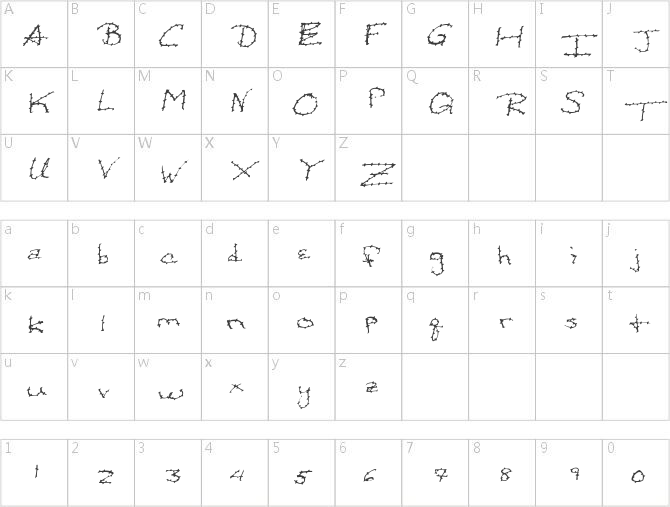
FZ HAND 24 SPIKED ITALIC
FZ HAND 24 SPIKED ITALIC介绍
FZ HAND 24 SPIKED ITALIC字体字库是一款让人赏心悦目、百看不厌的英文字体,适合各类广告和产品包装设计应用,字体大小0.09MB,格式为ttf字体,上传用户是welking,作者/版权方为未知